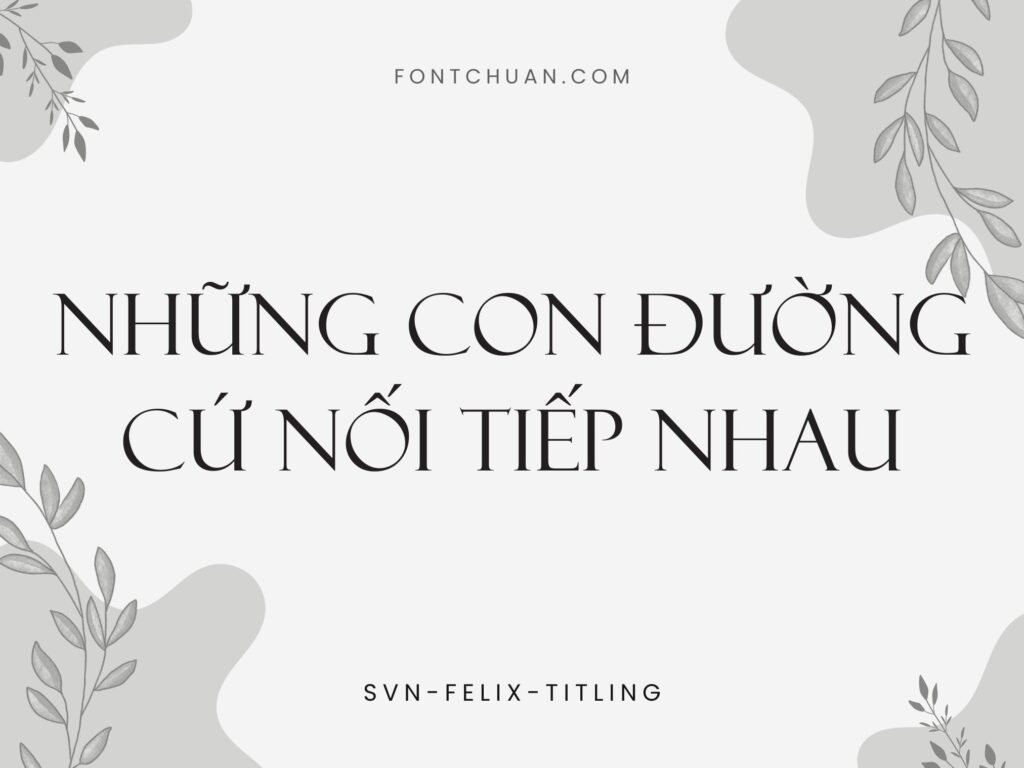
Font SVN Felix Titling Việt Hóa
Tác giả Font: Phillip Boydell
Font SVN Felix Titling là phiên bản Việt hóa của kiểu chữ Felix Titling, được thực hiện bởi Styleno.1 Fonts. Felix Titling là một kiểu chữ tiêu đề được thiết kế bởi Monotype Type Drawing Office vào năm 1934, dựa trên bảng chữ cái của nhà thư pháp và họa sĩ người Verona, Felice Feliciano, xuất hiện năm 1463 trong tác phẩm về chữ khắc La Mã. Font này chỉ bao gồm chữ in hoa, chữ số và dấu câu, mang phong cách cổ điển và hình học, lý tưởng cho các tiêu đề và thiết kế cần sự trang trọng.
SVN Felix Titling phù hợp cho các dự án thiết kế yêu cầu sự trang trọng và cổ điển, như tiêu đề sách, biển hiệu và các ấn phẩm quảng cáo. Các ngành nghề như quảng cáo và giáo dục có thể tận dụng font này để tạo điểm nhấn trong thiết kế. Ngoài ra, font cũng thích hợp cho các sự kiện như Tết và các lễ hội truyền thống.